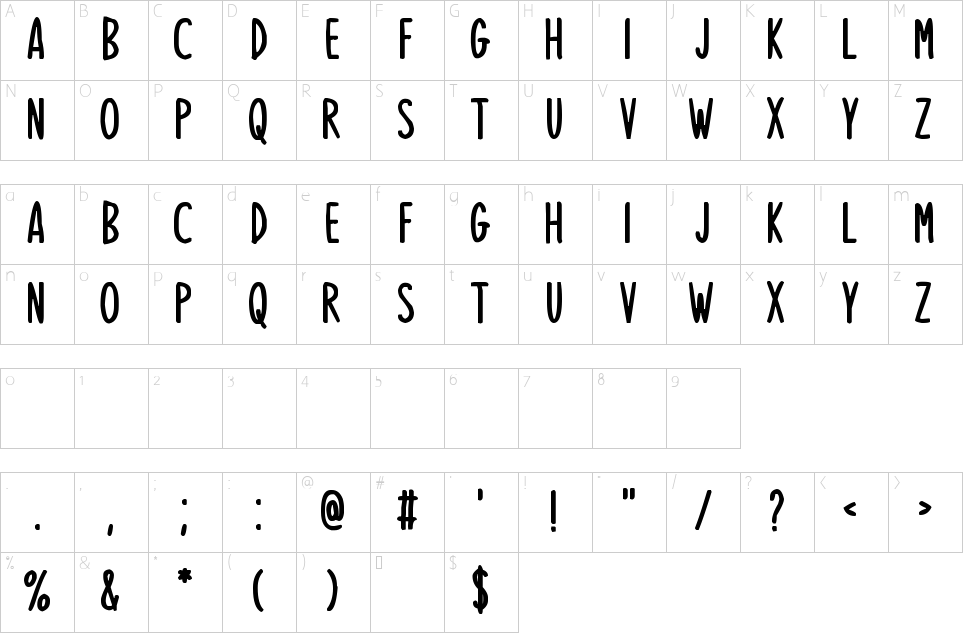
A fonte Journey Planner é uma deliciosa escolha para designers gráficos em busca de uma fonte fácil de usar e com um bom equilíbrio de linhas. Com seu design pensado para oferecer uma fácil leitura e uma boa legibilidade, Journey Planner é ideal para qualquer aplicação, desde o design de websites e o layout de e-mail até o design de materiais impressos. Esta fonte foi criada por Md. Shohail Bhuian e, até o momento, mais de 12.090 pessoas já a baixaram. Sem dúvidas, é uma ótima opção para aqueles que buscam fontes gratuitas e de alta qualidade. Junte-se à comunidade de designers que estão valorizando Journey Planner por sua simplicidade e excelente desempenho.